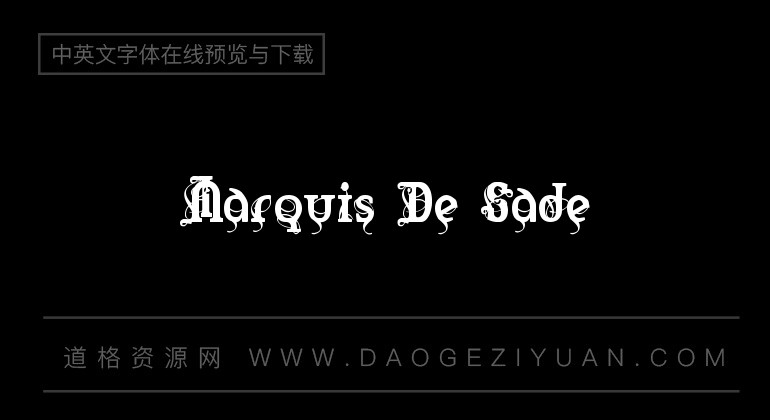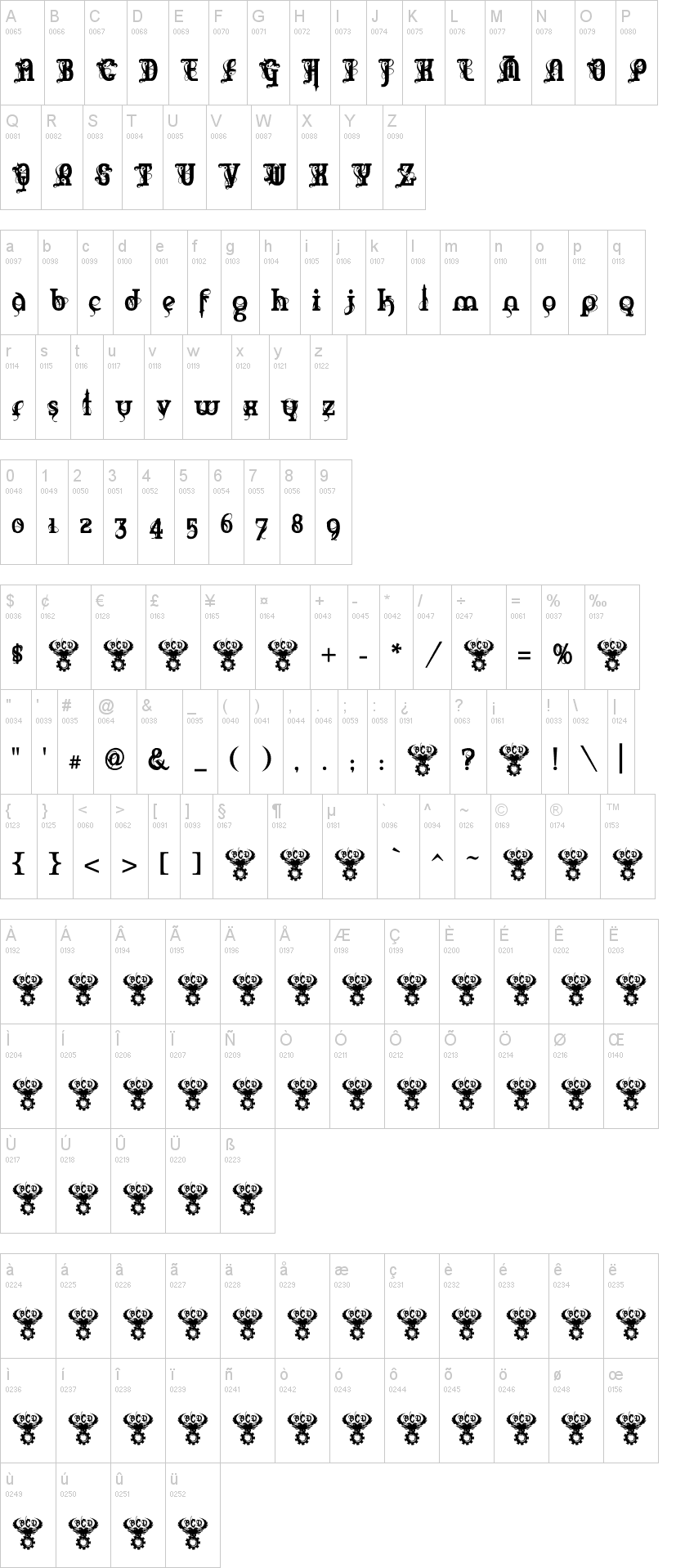
Marquis De Sade
Marquis de Sade 是一种装饰性的西文手写字体。其得名自18世纪法国小说家和哲学家马基雅维利·德·萨德(Marquis de Sade),因其文风激进而颇具争议。 这种字体的特点是书写时使用大量的弯曲线条和锯齿线条,给人一种古老、幽灵般的感觉。它适用于制作各种风格的海报、明信片、书籍封面等等。由于其古典和神秘的外观,Marquis de Sade 字体也常被用于元素和场景需要有一定神秘感的设计领域,如电影片头、音乐封面等等。 总之,Marquis de Sade 字体是一种充满魅力、神秘感和个性的装饰性字体,适用于各种不同的设计用途。
Marquis De Sade是一款非常不错的手写艺术字体,具有很好的视觉感,适合于文化类的宣传设计、商业类品牌的广告和产品包装设计以及个性化文字排版等较多场景。